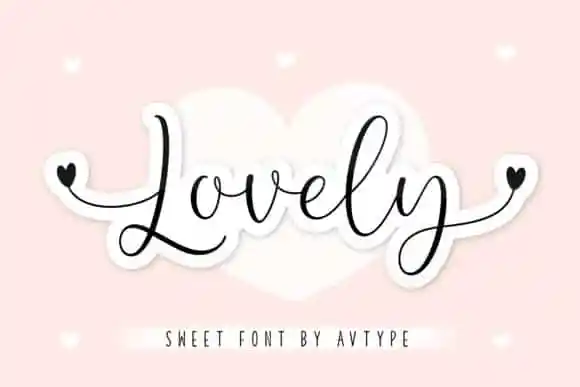
Lovely Display Font
A fonte ‘Lovely Display Font’ é uma maravilhosa opção para aqueles que buscam um toque autêntico e elegante em seus projetos digitais, seja ele para logotipos de luxo ou anúncios promocionais. Desenvolvida pela AV Type, esta fonte inovadora é ideal para criações criativas como branding, selos de casamento ou cartões de cumprimentos. O design originalmente inspirado em escrita a mão cria um efeito quase dançante nos caracteres, que se movem harmoniosamente ao longo da linha base. A vantagem deste tipo de fonte é que você pode acessar todos os gílios (caractéres) e swashes sem esforço algum, graças à sua codificação PUA. Com uma aparência elegante e vibrante, a ‘Lovely Display Font’ se destaca perfeitamente para aplicativos como design de logotipos, gráficos promocionais ou até mesmo para criação de cartões de cumprimentos personalizados. Seja você um designer profissional ou alguém que deseja adicionar um toque único aos seus projetos pessoais, esta fonte é uma escolha ideal para criar experiências visuais memoráveis e única. Sem dúvida alguma, ‘Lovely Display Font’ é a fonte perfeita para qualquer projeto que busque transpor emoção e elegância através do design de texto digital.